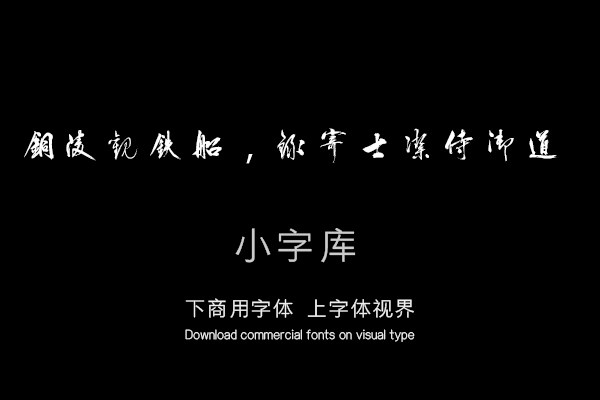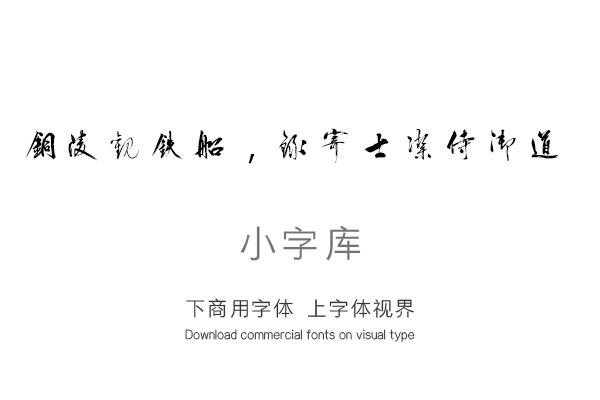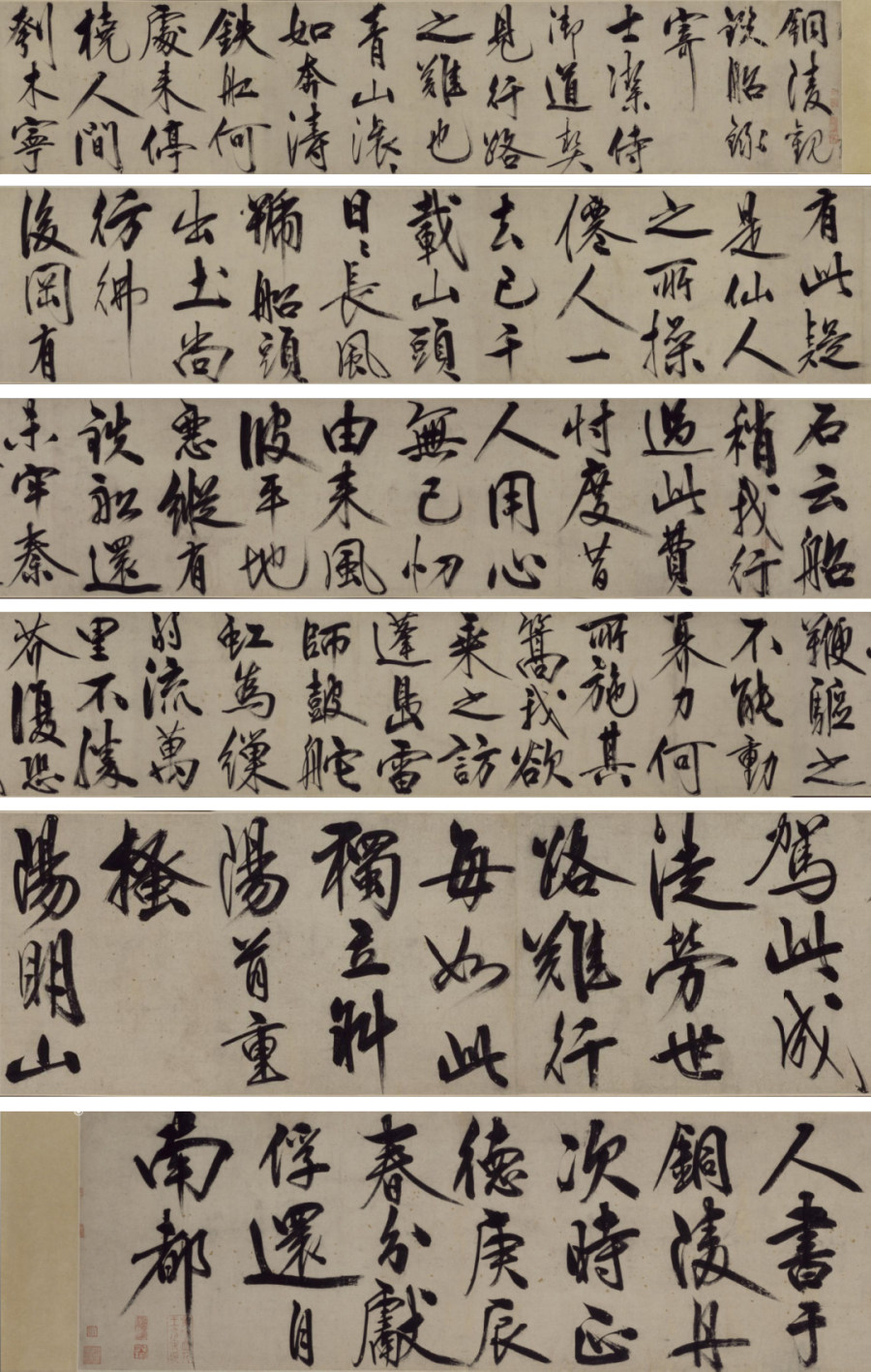
《汉标王阳明铜陵观铁船录寄》是一款根据明代王阳明《铜陵观铁船录寄》,经过作者临摹书写再次调整制作的小字库,该小字库共收录了该真迹作品中约209个字体。单字授权
铜陵观铁船,录寄士洁侍御道,契见行路之难也。青山滚滚如奔涛,铁船何处来停桡。人间刳木宁有此,疑是仙人之所操。僊人一去已千载,山头日日长风号。船头出土尚仿佛,后冈有石云船稍。我行过此费忖度,昔人用心无己忉。由来风波平地恶,纵有铁船还未牢。秦鞭驱之不能动,奡力何所施其篙。我欲乘之访蓬岛,雷师皷舵虹为缫。弱流万里不胜芥,复恐驾此成徒劳。世路难行每如此,独立斜阳首重搔。“阳明山人书于铜陵舟次,时正德庚辰春分献俘还自南都。”